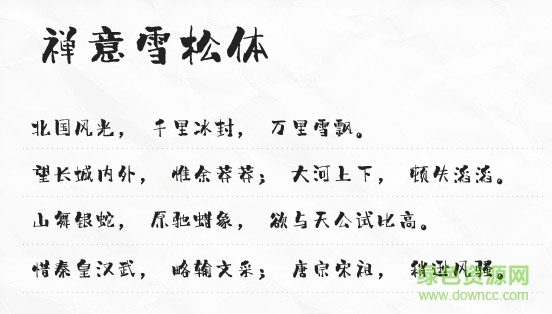
禅意雪松体字体
禅意雪松体字体专为艺术设计而生,该字体撇捺笔画粗壮,横竖笔画细腻,给人非常悠闲自在的感觉,可运用于手机主题,酷炫十足,欢迎到绿色资源网下载使用!
禅意雪松体是一款特色十足的中文字体,具有西方手写字的特色,你可以将其用于海报设计、杂志设计、涂鸦设计等方面。同时字体俊逸洒脱,美观又实用,深受艺术创作、排版印刷、编辑设计等行业人士喜爱!